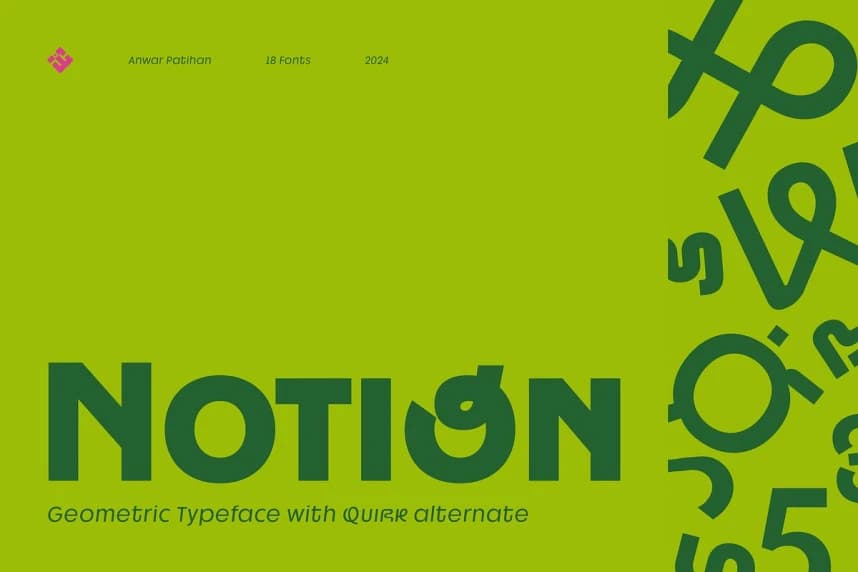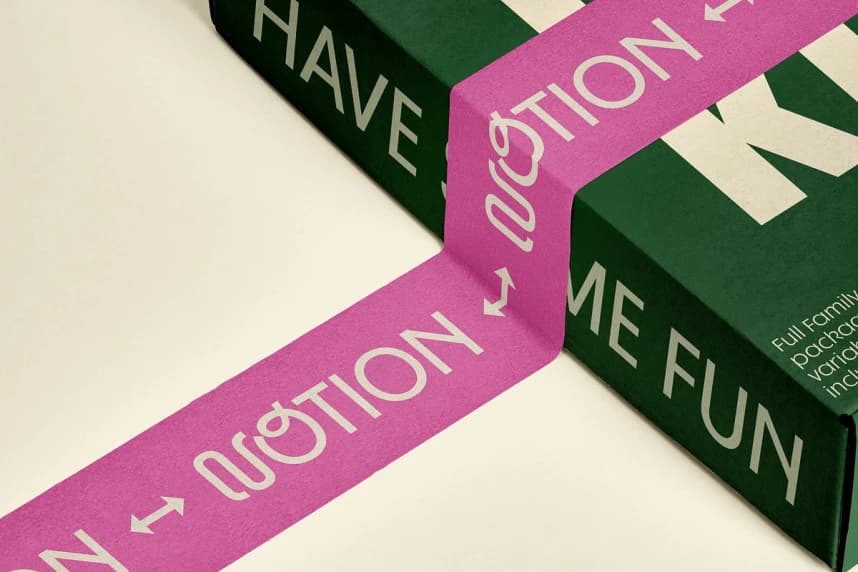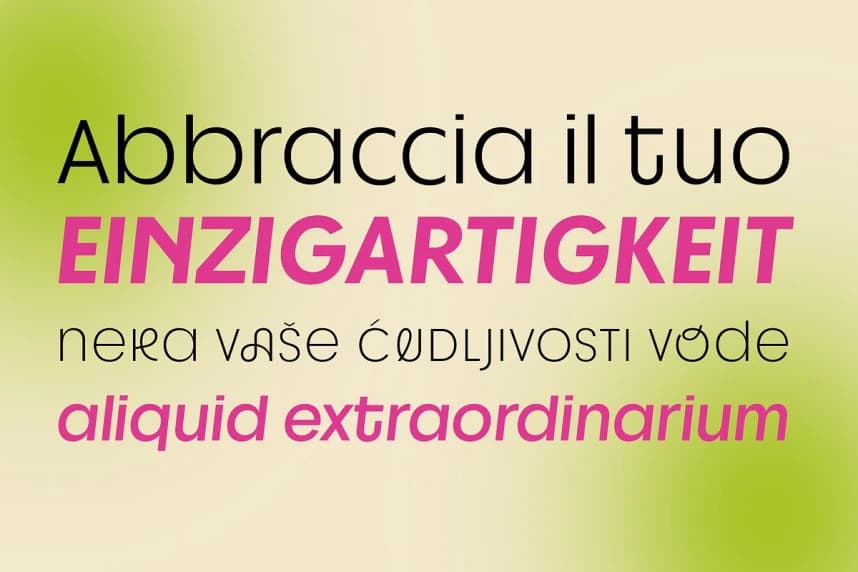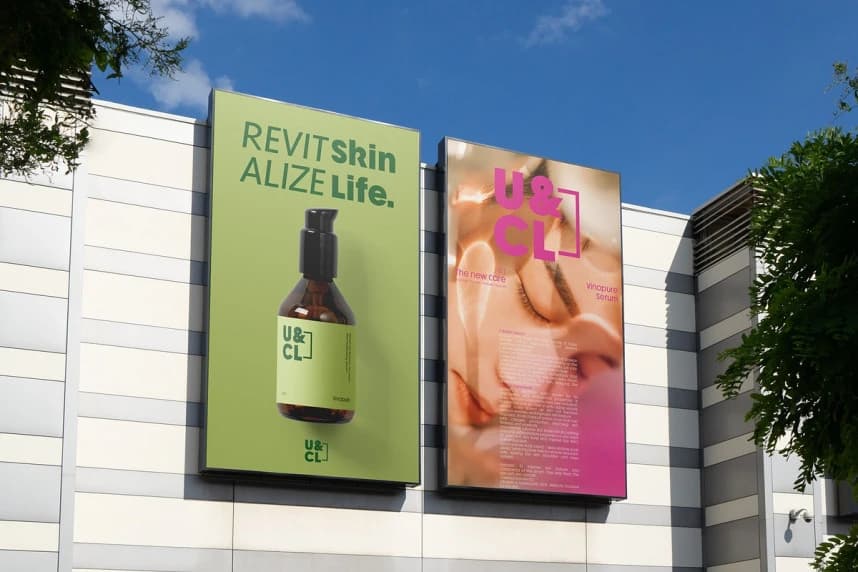
JHC Notion Font, hassasiyet ile kişilik arasında mükemmel bir denge kuran modern bir geometrik sans-serif yazı tipidir. Temiz, keskin hatları ve minimalist yapısıyla çağdaş bir hava yayar; bu da onu pek çok proje için çok yönlü kılar.
JHC Notion Font, modern geometrik sans-serif bir yazı tipidir ve hassasiyet ile kişilik arasında mükemmel bir denge kurar. Temiz, keskin hatları ve minimalist yapısıyla çağdaş bir hava yayıyor ve bu da onu çok çeşitli projeler için çok yönlü kılıyor.